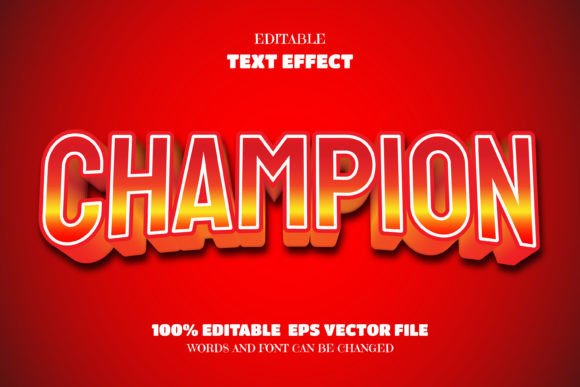
Champion Text, Editable Font Effect
Die richtigen Designelemente zu finden, kann eine Herausforderung sein, aber Champion Text, Editable Font Effect bietet eine außergewöhnliche Sammlung, die Ihre Arbeit sofort aufwertet.